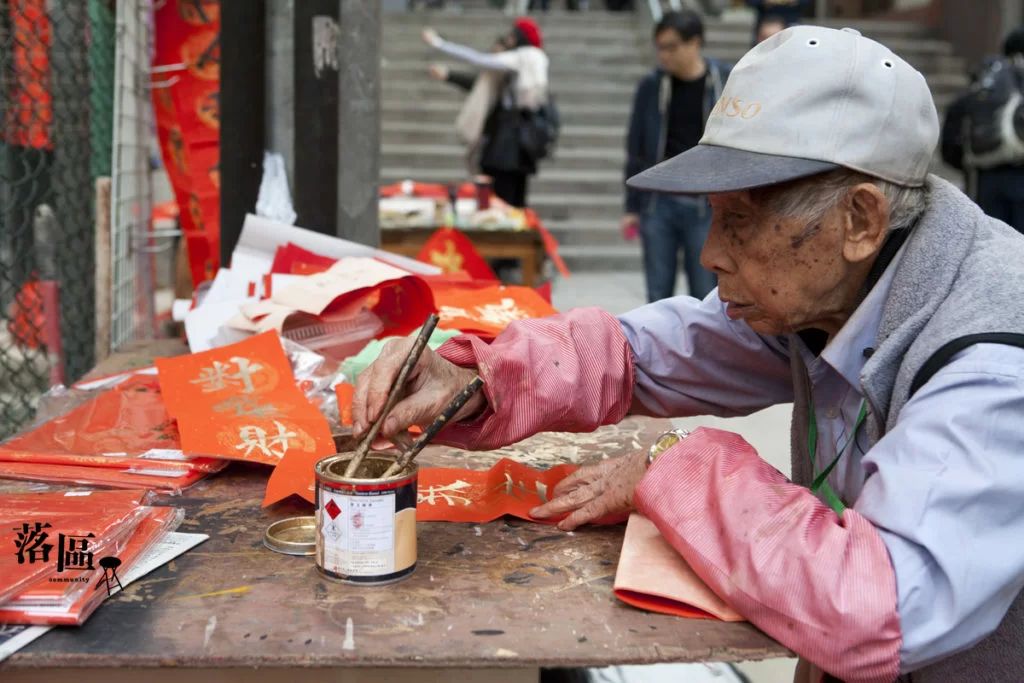
【落區】春風吹 又見金漆揮寫「靈氣」揮春 -弓絃巷93歲添叔
添叔、紅紙、毛筆、金漆、揮春,構成上環摩羅上街(古董街)接連之弓絃巷的一道風景,新春前這道風景多添一條等候他揮毫新年願望的人龍。用餐刀代鎅刀裁切紅紙,揮春不論大小都用同一支筆,把寫好的揮春攤在地上放乾,隨手拈來的鉸剪拉呎油漆蓋,甚至路邊的磚頭木條,都是臨時紙鎮。成件事好raw,好街頭,好庶民,好貼地。
年年初三都係我生日!
他眼神堅定地說:「寫字係我精神食糧,可以行氣活血,你有無見我手震呀?」記者信,真係信。每逢正月初三就大一歲的添叔,今年已經九十有三,具有相對年紀異常充足的中氣,相對年紀極度清晰的思路,相對年紀十分矯健的步伐。如果說寫字養生,他就是活見證。
採訪當日是年廿一,記者一行三人在他的書法檔逗留了近五個小時,有八成時間為添叔充當書僮,助他裁紙、提示他要寫甚麼揮春、把寫好的掠乾、點算揮春數目、應付客人查詢,因為這一天,他接到一單四千三百元的大生意,要寫近七十張大大小小的對聯、揮春及合體字門貼,重點是客人希望他兩小時左右起貨。這位帶點霸氣但有禮貌的太太強調:「其他有啲人寫平啲㗎,不過我都係鍾意你手字。」
雖說他相當精靈,畢竟突如其來的客人太多,要求又五花八門,任誰也手忙腳亂,何況他是個九旬長者。不過即使準備過程如何「甩轆」,落筆之時他總是不徐不疾,從容完成一張又一張,而且筆鋒帶勁。佻皮的他不忘認叻:「你睇我寫呢四張身體健康,四張都唔同字體㗎!草書、楷書、行書、隸書。」
挨年近晚,一大班老主顧蜂擁前來。一位看來富泰的太太氣沖沖走來道:「你做乜唔聽電話,以為你休息呀,幾驚呀。我間藥房年年搵你寫一大張『生意興隆』㗎嘛﹗」客人的焦急不安,顯示了這張揮春對他們的重要。觀察了半天,光顧的都異口同聲表示:「年年搵佢寫」。他忙得買了下午茶熱狗都沒時間吃。記者不時問他會否肚餓,他總是答:「一陣先,寫完先食。」
筆走龍蛇八十載
強調「寫極都唔厭,越寫越精神」的他筆走龍蛇八十多年,七八歲在廣州幫當中醫的契爺磨墨,字是看懂的,不是學懂的,更漸漸愛上習字。「佢要寫毛筆字開藥方,我就喺旁邊睇。」後來來到香港,他在金鐘的船廠做學徒。「打仗呀,要幫日本仔做嘢,因為我識字,溝通到,佢哋當我半個翻譯咁。」和平後,他在弓絃巷開檔賣眼鏡,配上平實店名:添記眼鏡。「我係視光師來㗎,我檔口掛咗個牌㗎!」說時自信滿滿,眼角會卡通式「叮一聲」那種。
六十年代他看到不少人新春前在古董街一帶擺檔寫揮春,他也貪得意跟着擺,後來有了熟客,就在檔口寫。對於自己有五湖四海慕名而來的人客,零舍自豪。「日本人、韓國人都搵我寫,仲有啲帶古玩來賣嘅北京人。」他稱客人歡喜他的揮春,是因為有神明加持。「我個檔口係龍口位,近文武廟,啲靈氣呀灑落啲揮春度呀。」靈氣難以測量,但記者相信大部分年復年幫襯的,都因為喜歡這位長壽老人蒼勁有力的大字。
入黑了,他尚有三副對聯要寫,街燈光線微弱,攝影師為他打燈照明。寫了一副,他終於翻出下午茶,三扒兩撥啃掉,提起精神把餘下的寫完,終於有時間跟我們談了幾句。
再三強調,添叔雖然壯健,但一次過用神寫這麼多張,不辛苦就假。日落黃昏,添叔手有微顫,明年想找添叔寫字,請早!